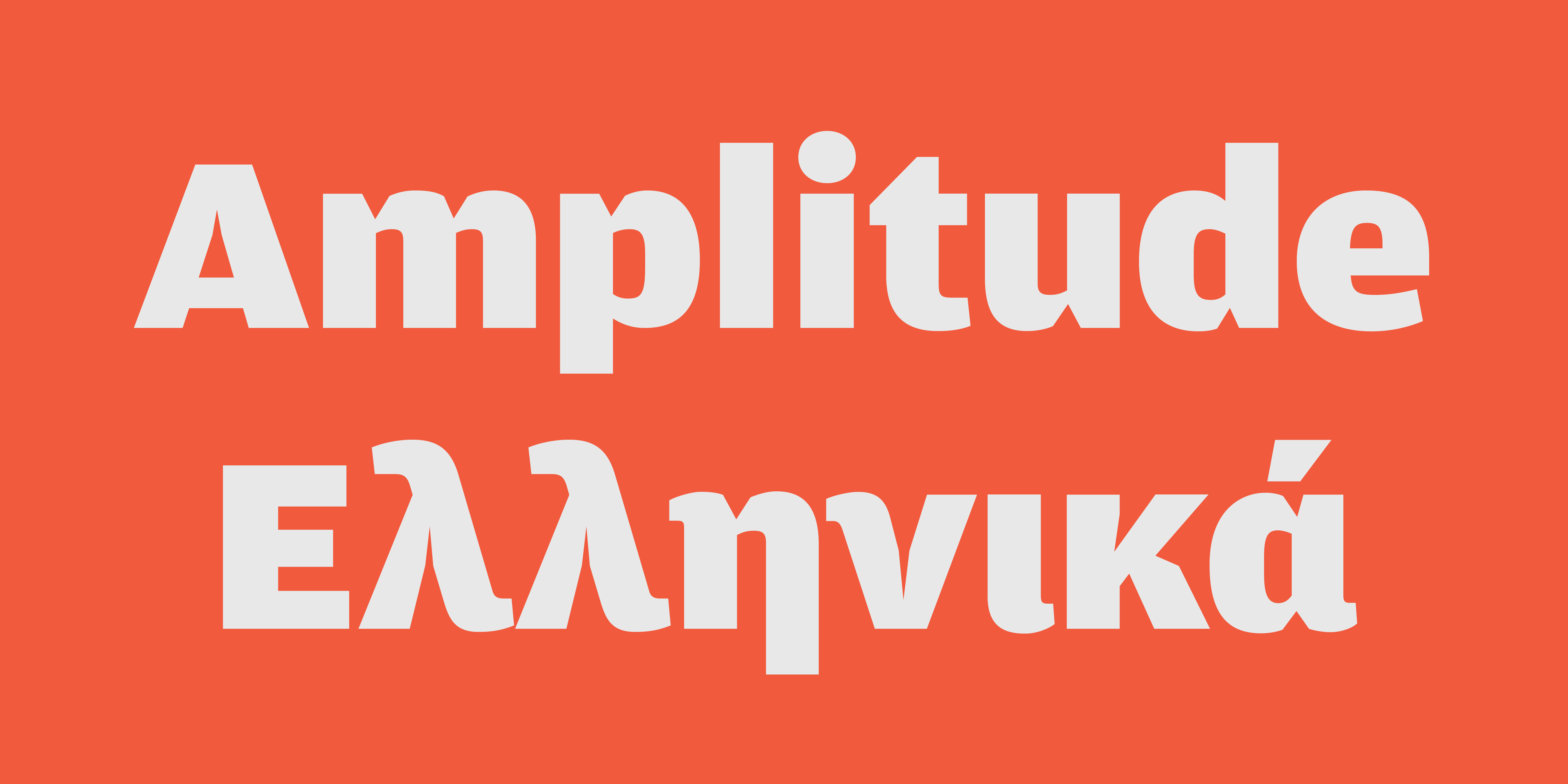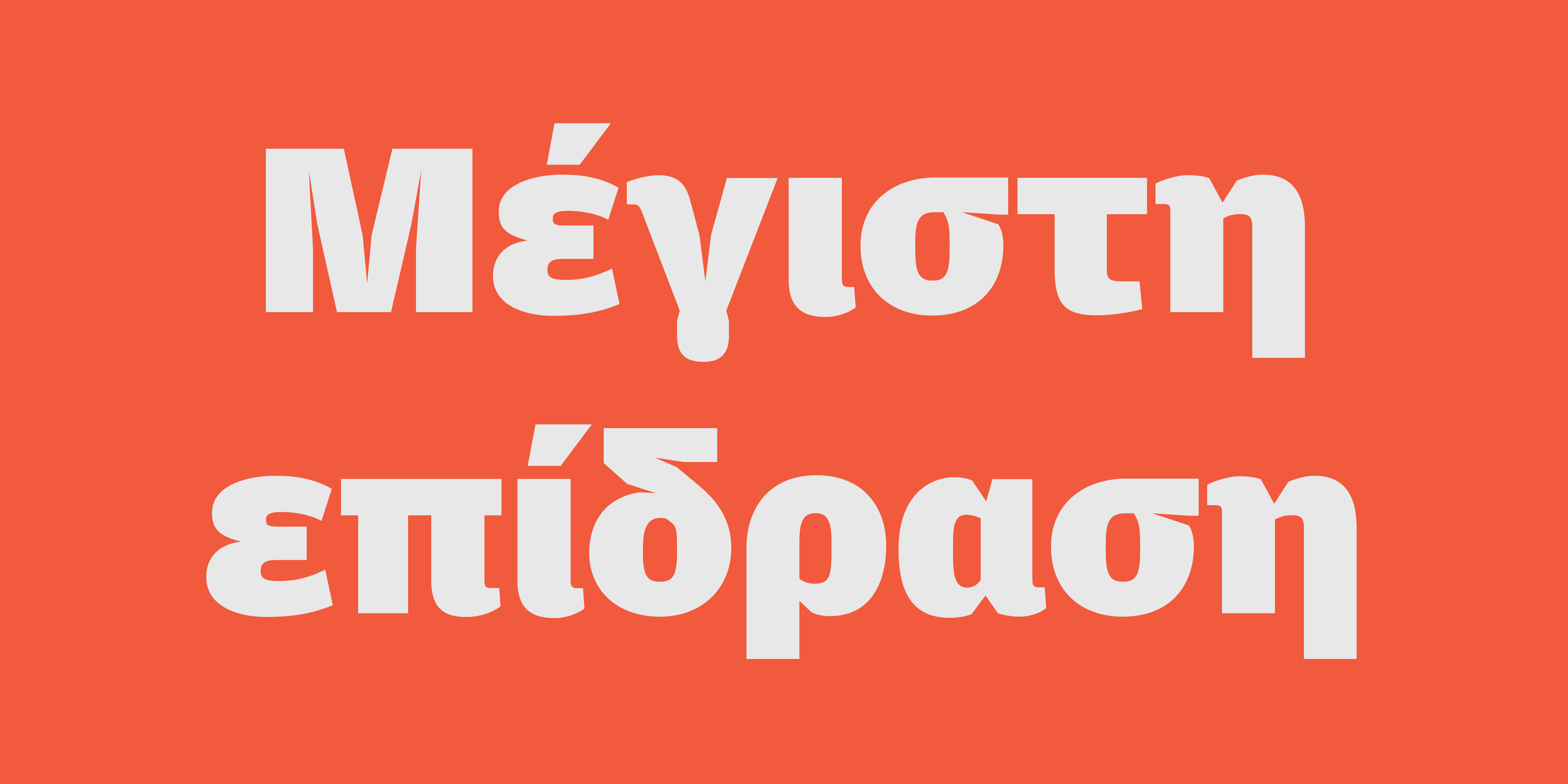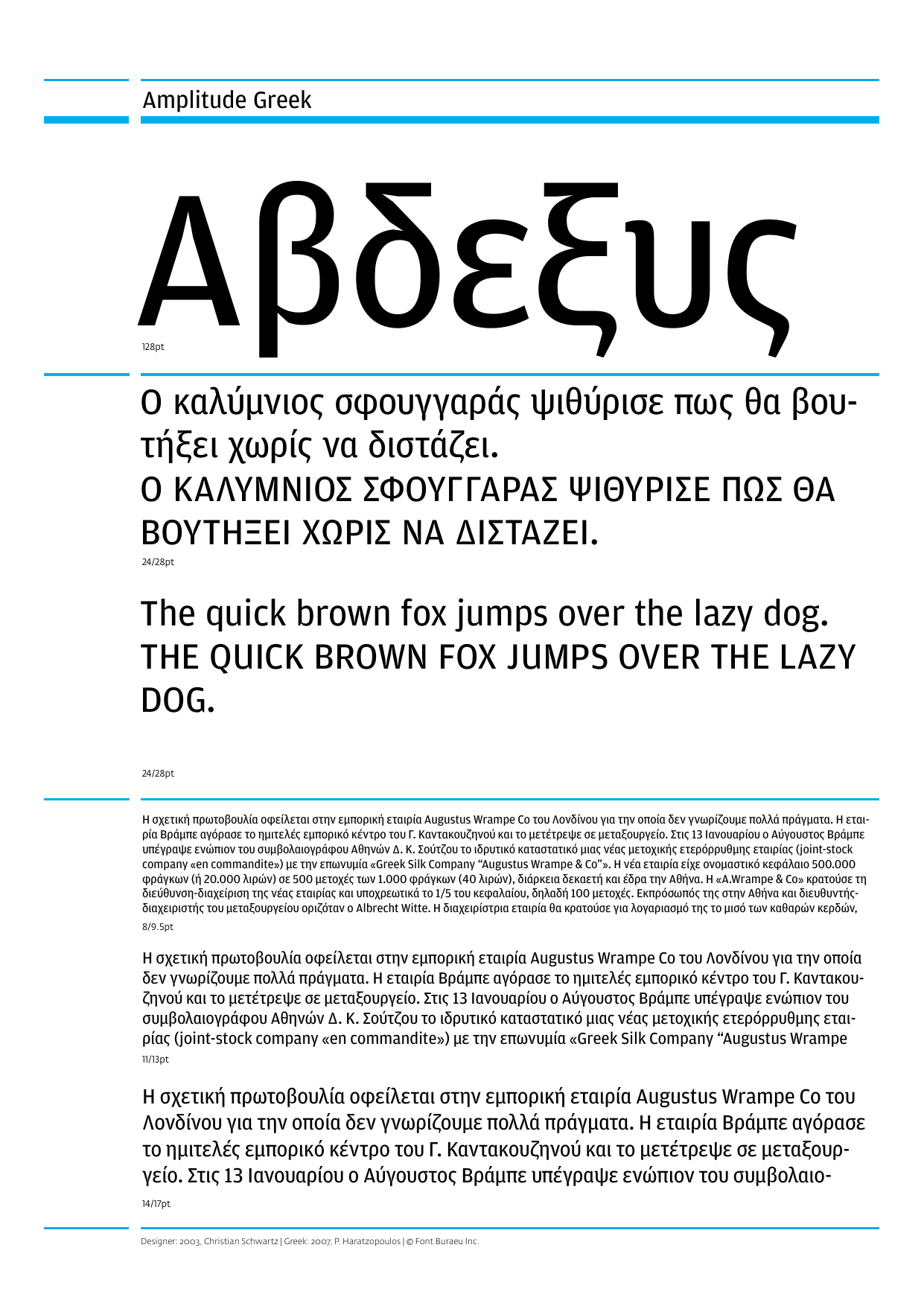
Amplitude Ελληνικά Collection
Μία επιτυχημένη γραμματοσειρά για χρήση σε μικρά μεγέθη στιγμών, οφείλει να προβλέπει την υπερχείλιση του μελανιού στο χαρτί και να κρατά αποτελεσματικά την ευαναγνωσιμότητα ακόμα και σε μη ιδανικές συνθήκες εκτύπωσης. Γοητευμένος από τις οπτικές εκφάνσεις αυτών των τελείως πρακτικών αντισταθμίσεων που λέγονται ink traps, ο Christian Schwartz σχεδίασε τα Amplitude, μία εκτεταμένη οικογένεια, χωρίς πατούρες, για κείμενο και τίτλους, η οποία μετατρέπει την πρακτικότητα σε στυλ: βαθιά γωνιακά κοψίματα που κάνουν τα μικρά μεγέθη ευανάγνωστα, ενώ παράλληλα προσθέτουν χαρακτήρα στα μεγέθη των τίτλων. Η Amplitude είναι σχεδιασμένη για να συμπεριφέρεται όπως δύο διαφορετικές γραμματοσειρές όταν φαίνεται σε διαφορετικά μεγέθη. Στα μεγέθη τίτλων οι λευκές αντιφόρμες προσδίδουν ένα ξεχωριστό ύφος, ενώ σε μικρά μεγέθη κάνουν τα κειμένα περισσότερο ευανάγνωστα. H ιδιαιτερότητα έχει τη βάση της στην πρακτικότητα. Σχεδιαστής Christian Schwartz, Ελληνική έκδοση Παναγιώτης Χαρατζόπουλος